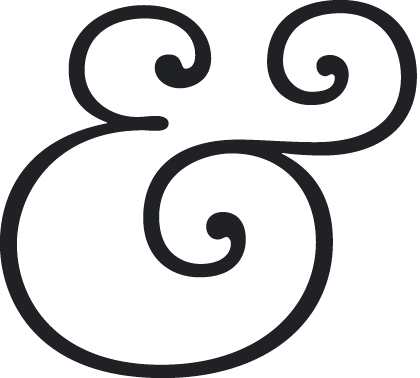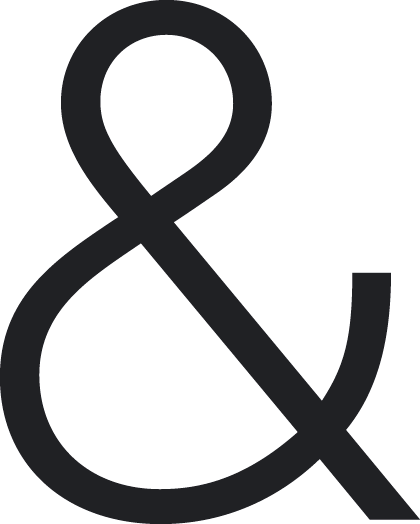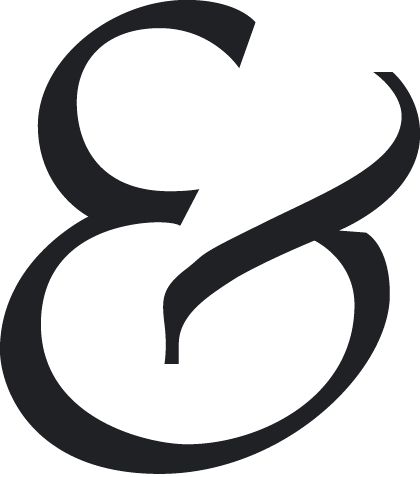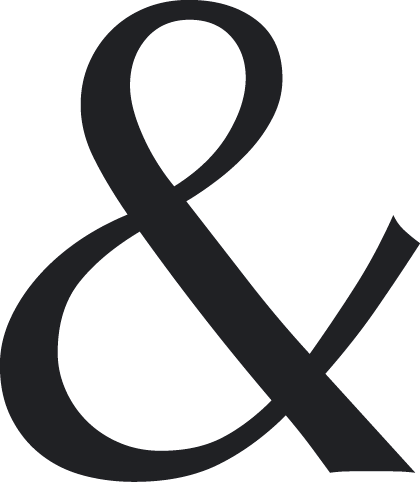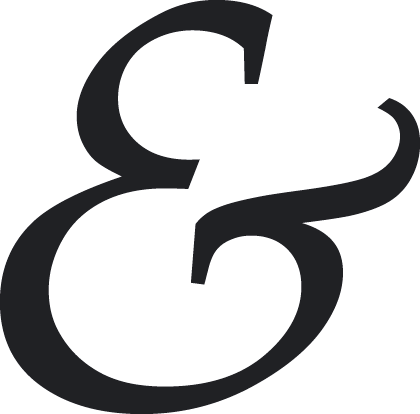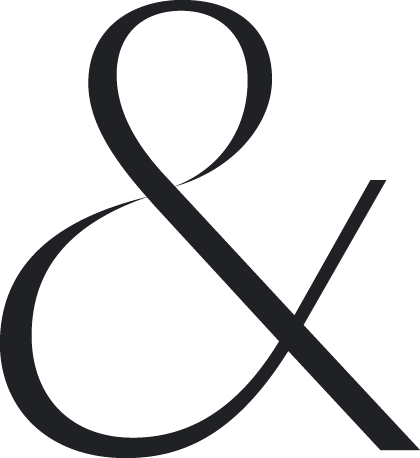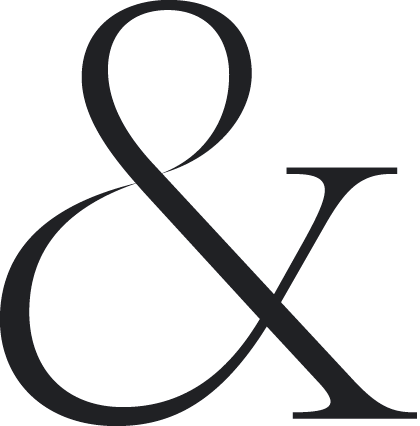
typoGraphie | Mes plus belles Esperluettes
Ce qui me connaissent savent que je suis un passioné du signe et de son organisation. Ci-dessous l’un des symboles le plus usité dans les courriers commerciaux et identités d’entreprise très *old-school*, l’esperluette. Il est né curieusement à peu près au même moment que le signe de l’arobase *@* c’est à dire entre le XVe et le XVI siècle. Curieux n’est-ce pas que l’arobase date du siècle de la Renaissance alors que chacun imaginait sa naissance avec celle de l’internet et de la toile.
Les signes ci-dessous proviennent de polices de caractères assez courantes puisque vous les avez presque tous sur vos ordinateurs. Regardez bien dans vos polices systèmes. Et observez le dessin de ces esperluettes qui font assaut d’élégance et de charme propre à habiller vos futurs mises en page. Un délice de formes, façon fer forgé pour l’ITC American Typewriter dessiné par Tony Stan, ou de rigueur pour la Din et de puissance institutionnelle pour l’Optima ou le Michelangelo (de Michel Ange) dessinés par le très grand Hermann Zapf. Nous avons choisi de montrer en dernier deux nouvelles polices de la Fonderie BP, les SangBleu, dessinés avec brio par Ian Party. Un florilège de délicatesse et de bon goût à la Française (bien qu’il exerce en Suisse). Vous aimez? n’hésitez pas à nous dire vos préférences :-)
ITC American Typewriter Alternate Light by Tony Stan
Din by Albert-Jan Pool & Achaz Reuss
Michelangelo by Hermann Zapf
Optima by Hermann Zapf
Palatino Italic by Hermann Zapf
SangBleuSans BP by Ian Party
SangBleuSerif BP by Ian Party